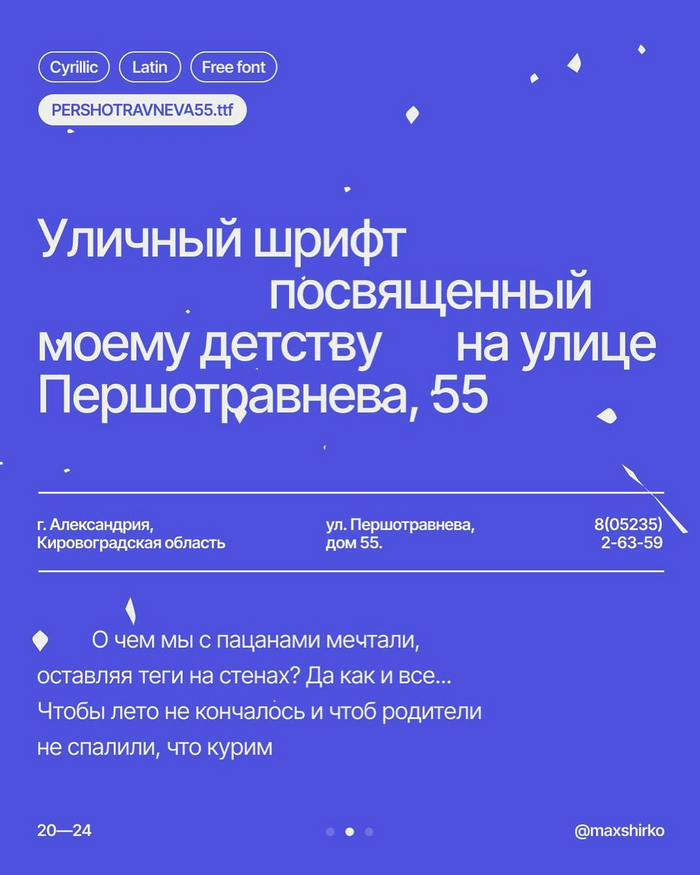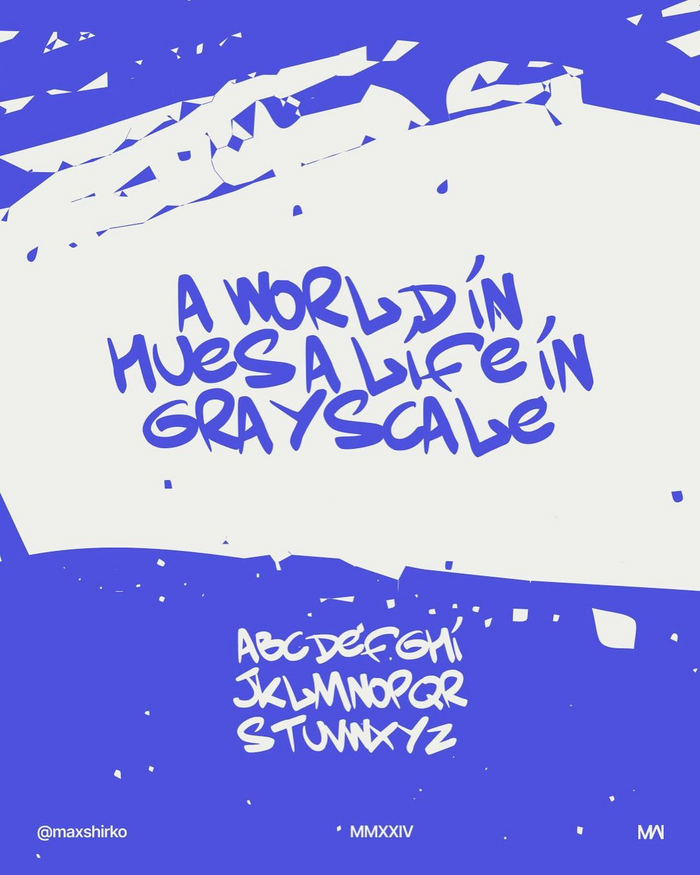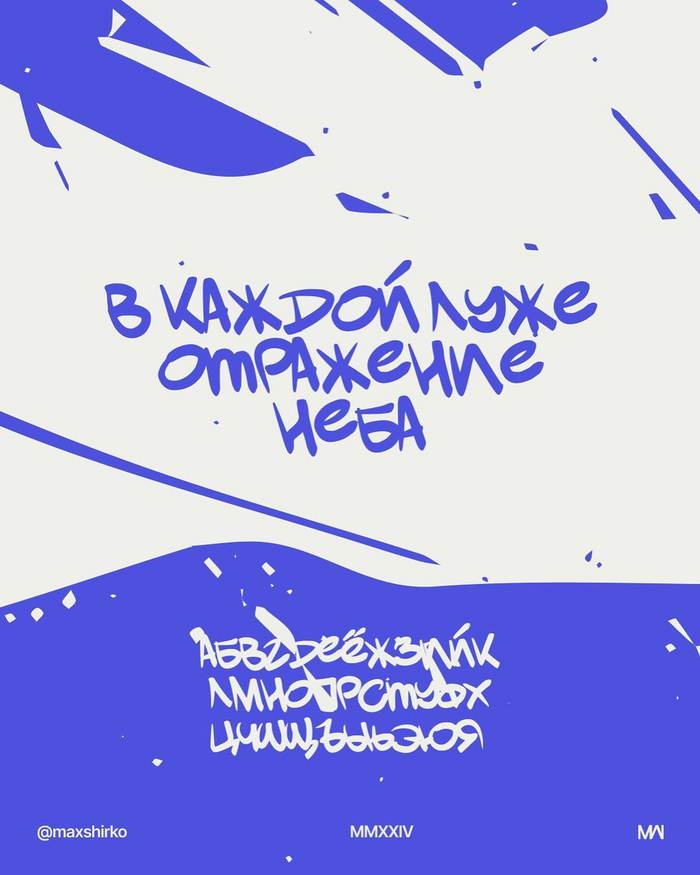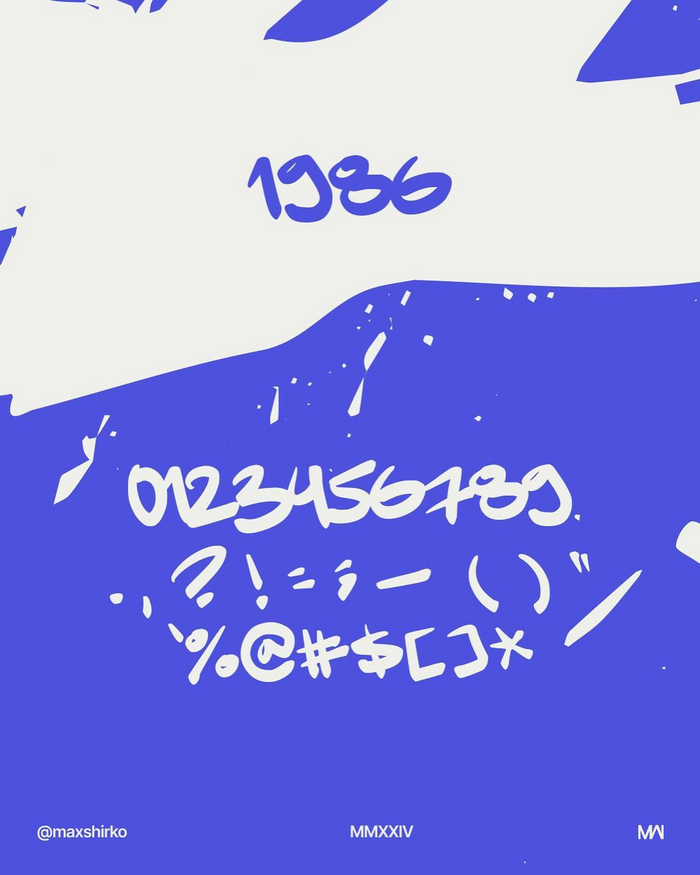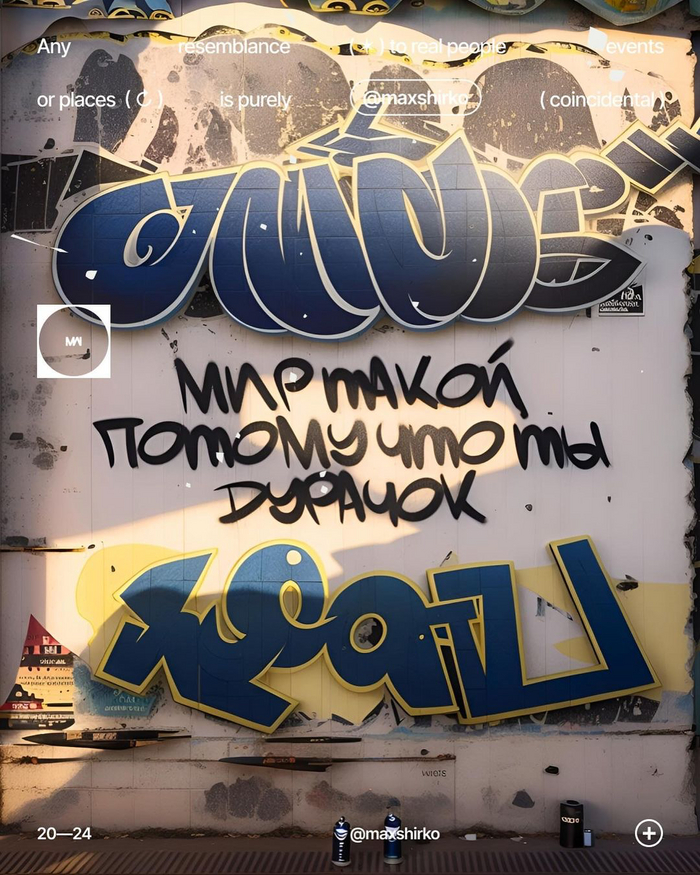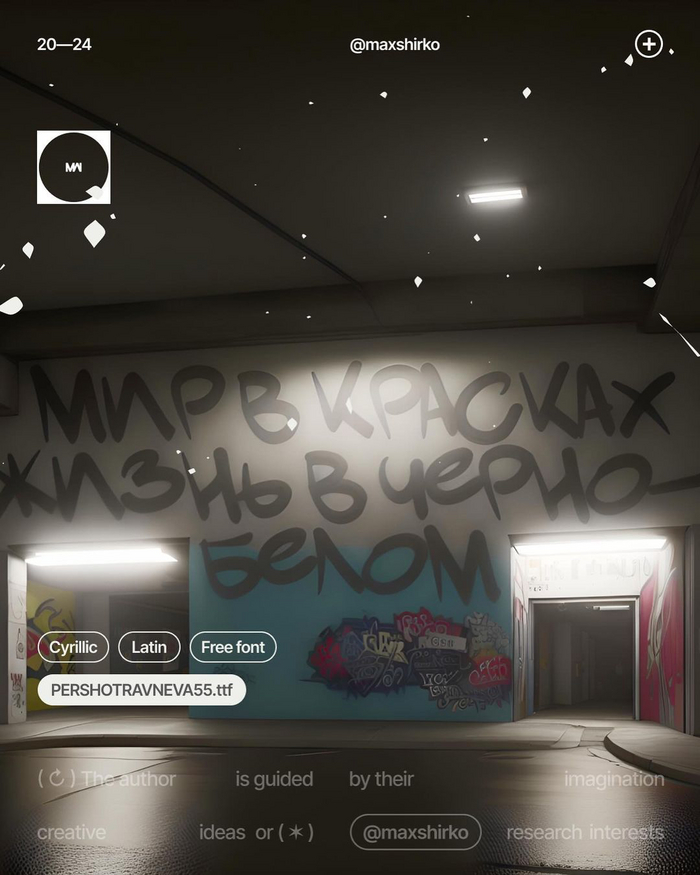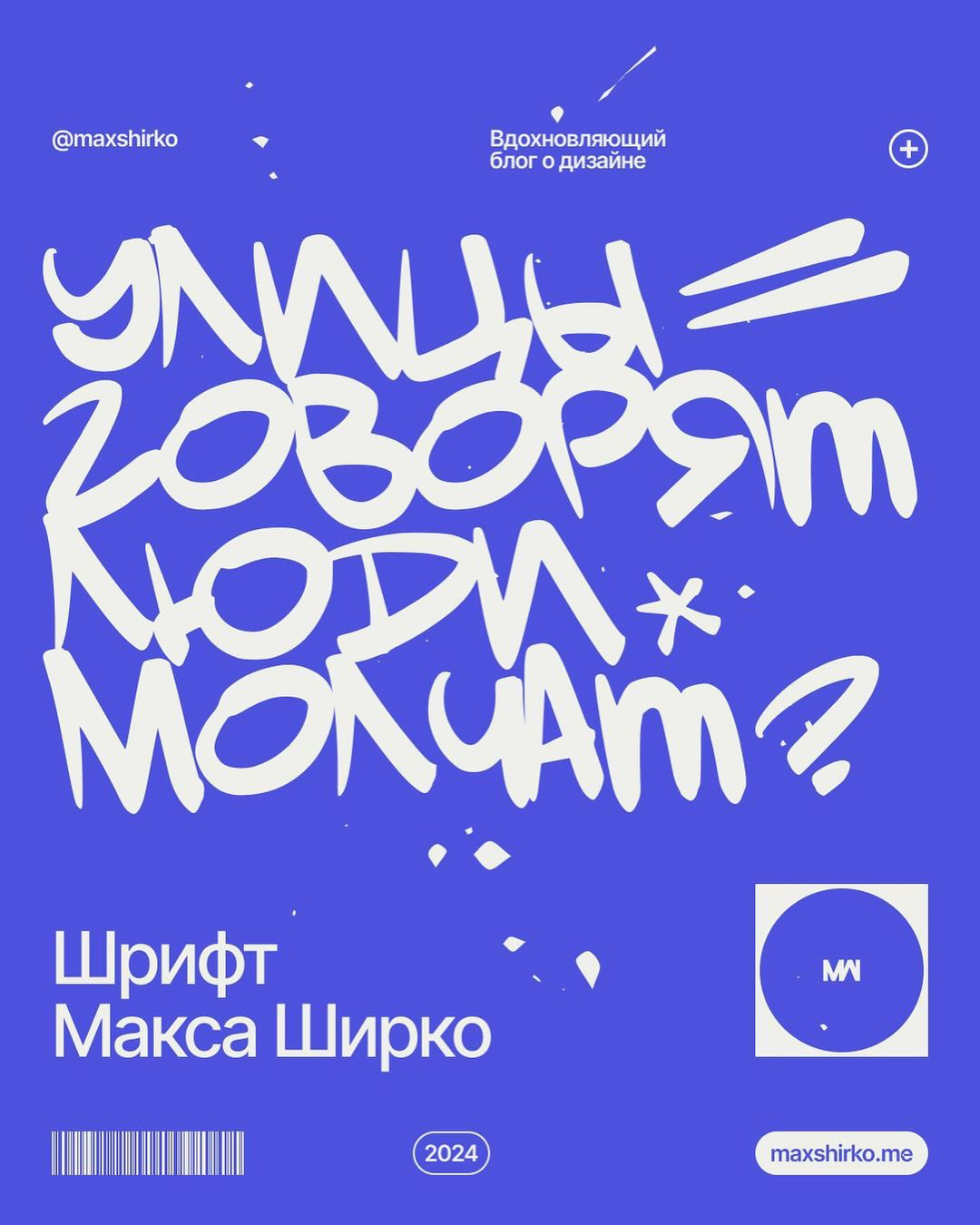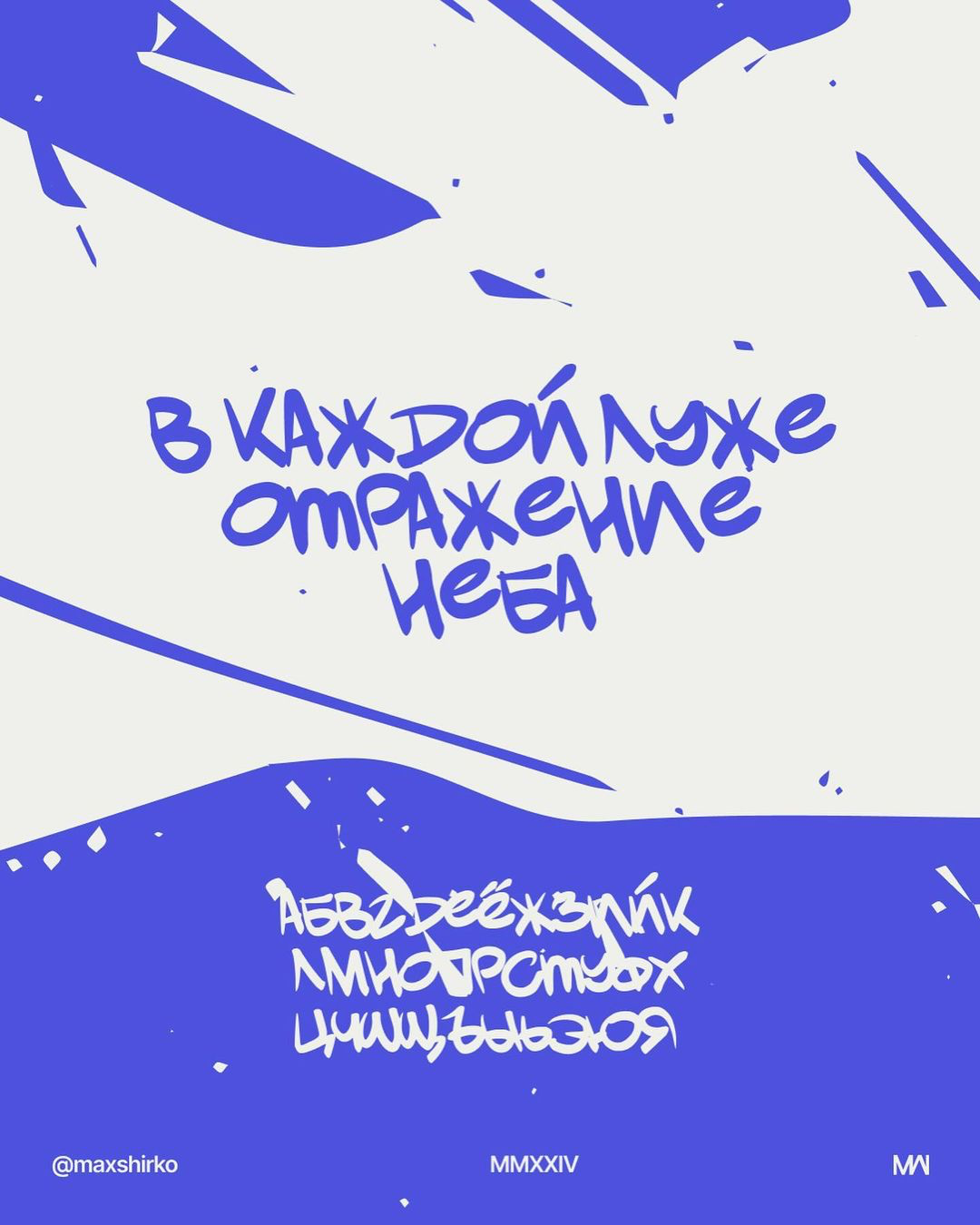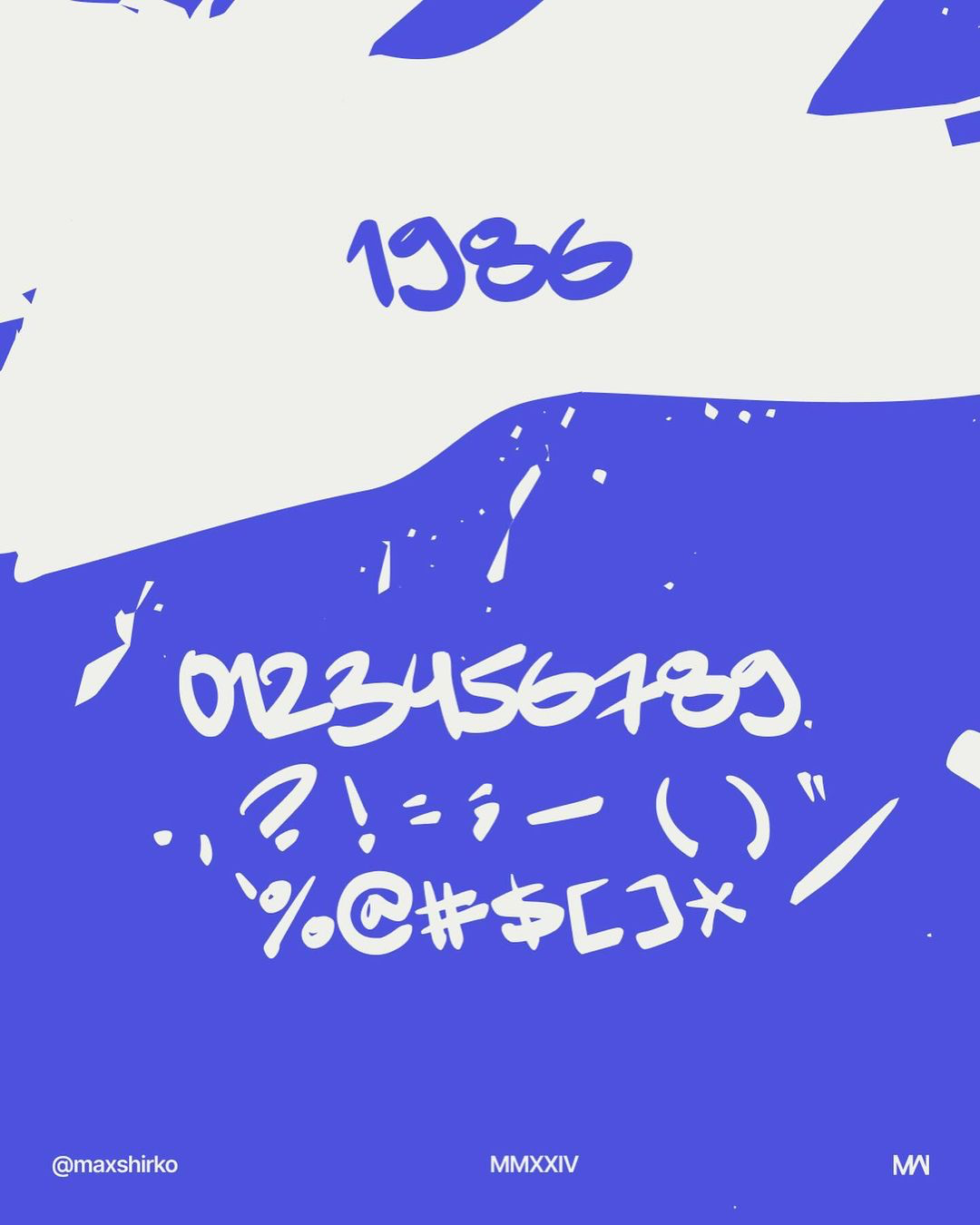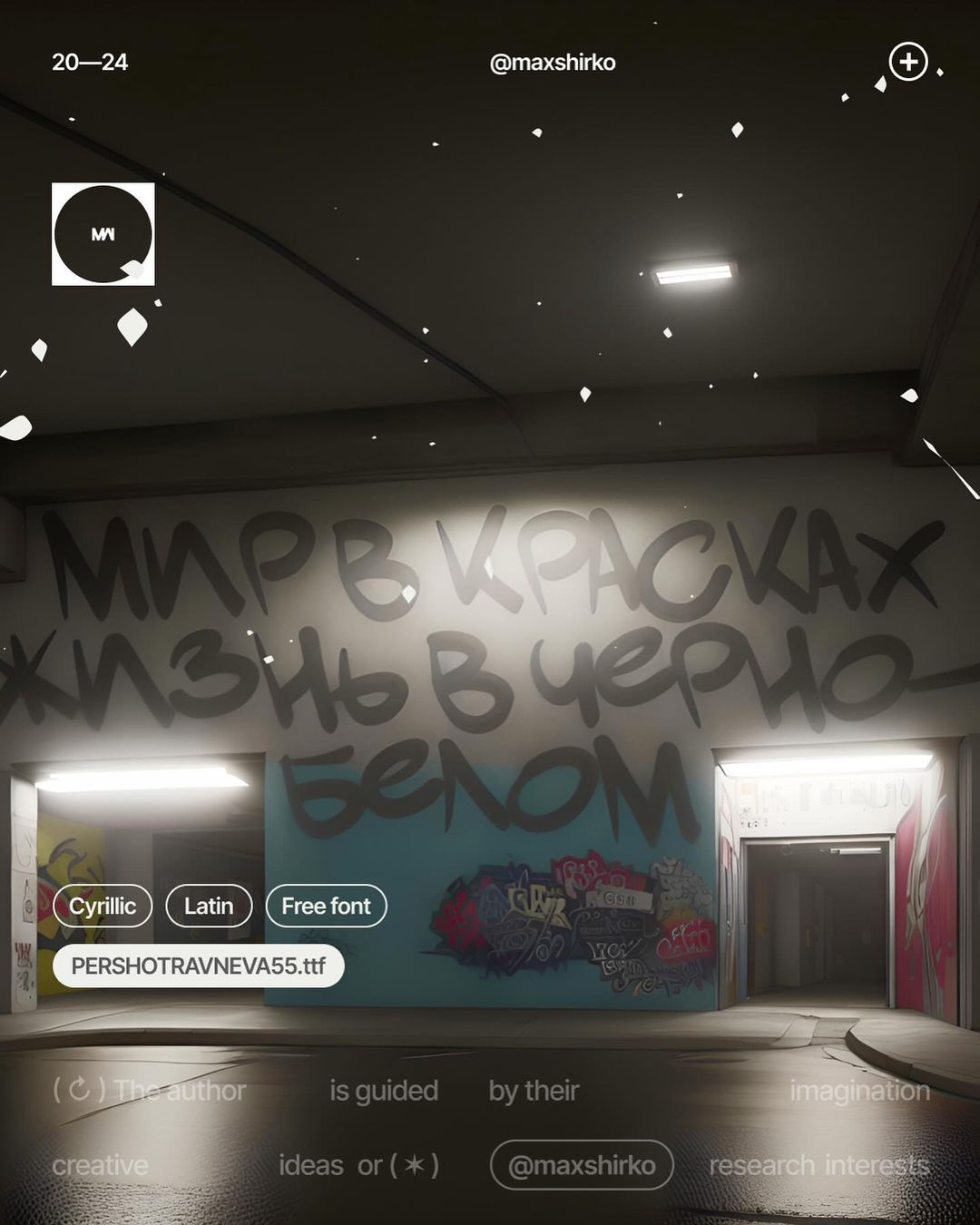
Шрифт Pervomayskaya55
От автора: Сделал шрифт для себя, но дарю его всем и каждому.
Это что-то из обрывков воспоминаний о тегах на стенах, о исписанных полях в тетрадках, любимых маркерах и несбывшихся мечтах рисовать стритарт. Акцентный, наглый, бунтарский и наивный шрифт Pervomayskaya55